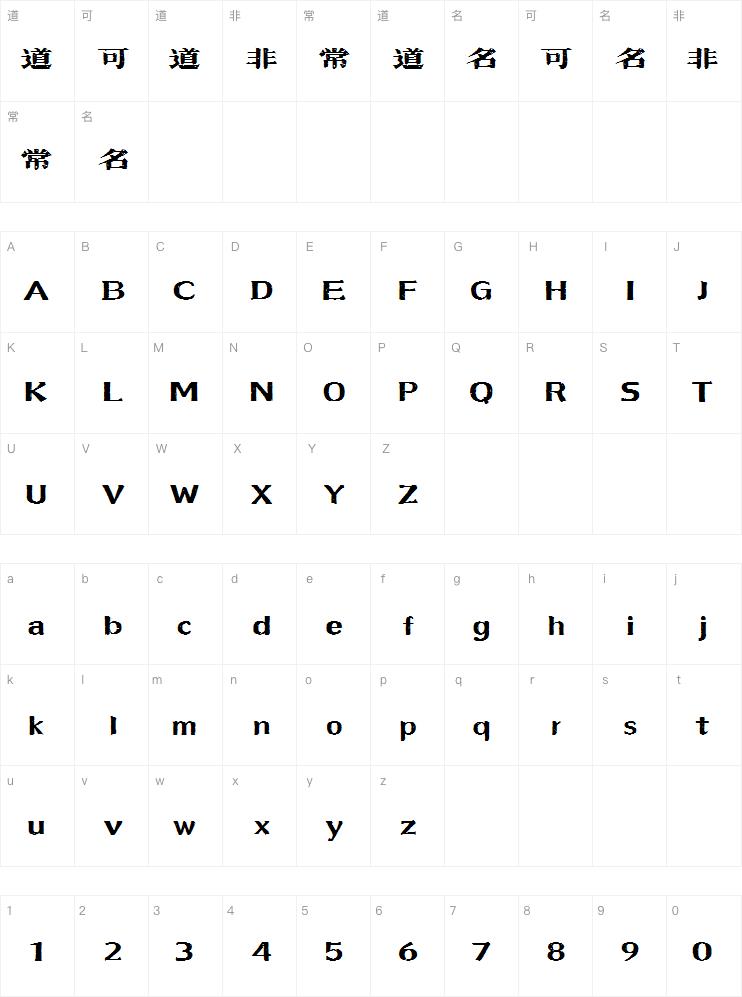
上首怀旧体,定位于复古怀旧风格。在设计过程中,深入研究了传统手写字体以及旧报纸、老书籍上的印刷字体特点,提取其中的经典元素并加以创新演绎。字体整体呈现出一种历经岁月沉淀的质感,笔画带有自然的磨损痕迹,仿佛承载着时光的故事,能够迅速将观者带入到怀旧的氛围之中。适用于搭配标志、广告标语、商业广告等高端属性。